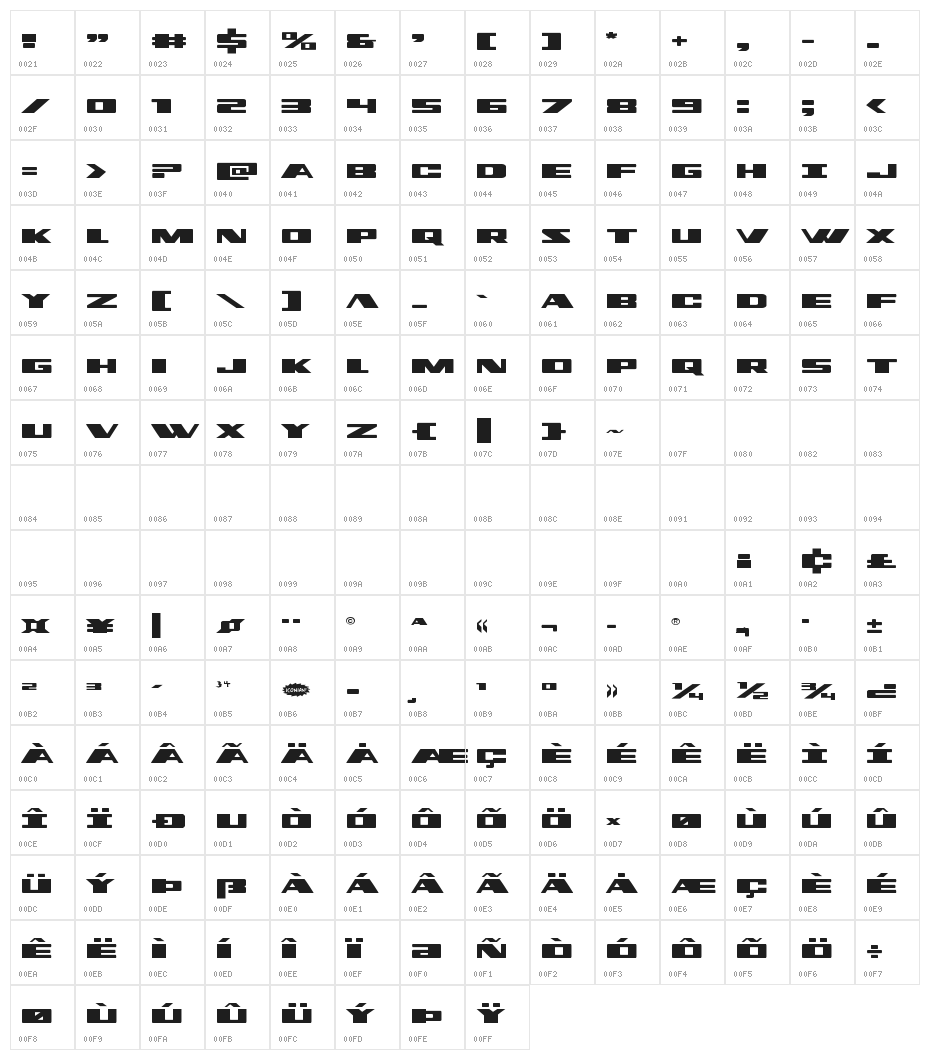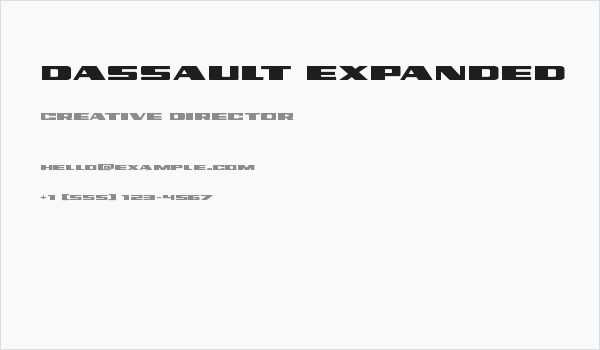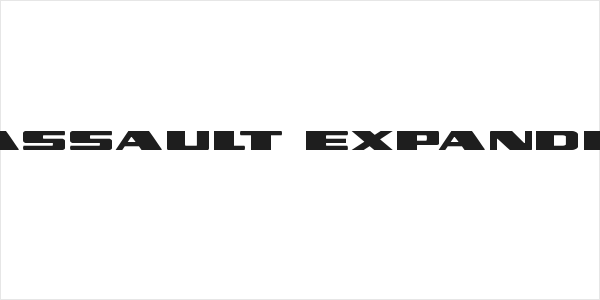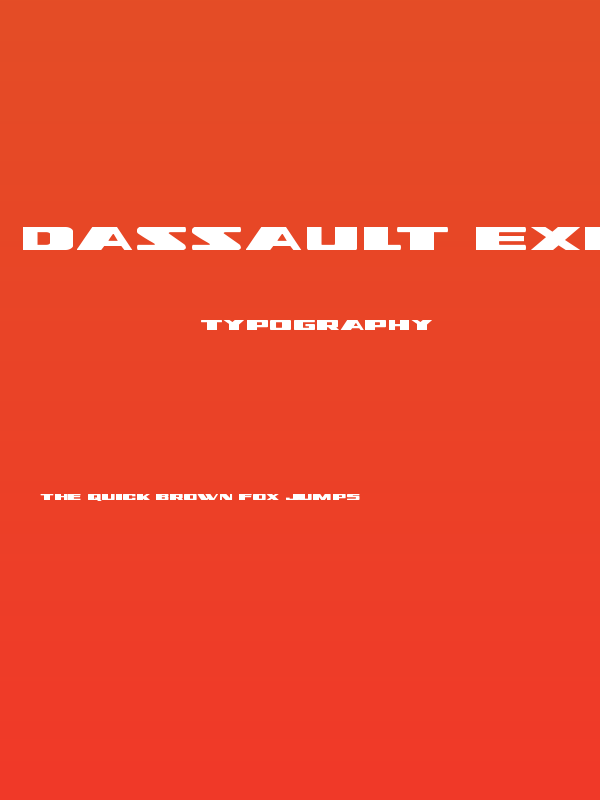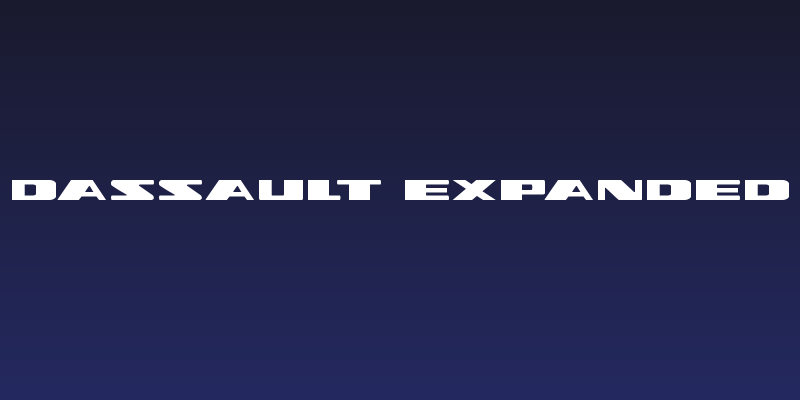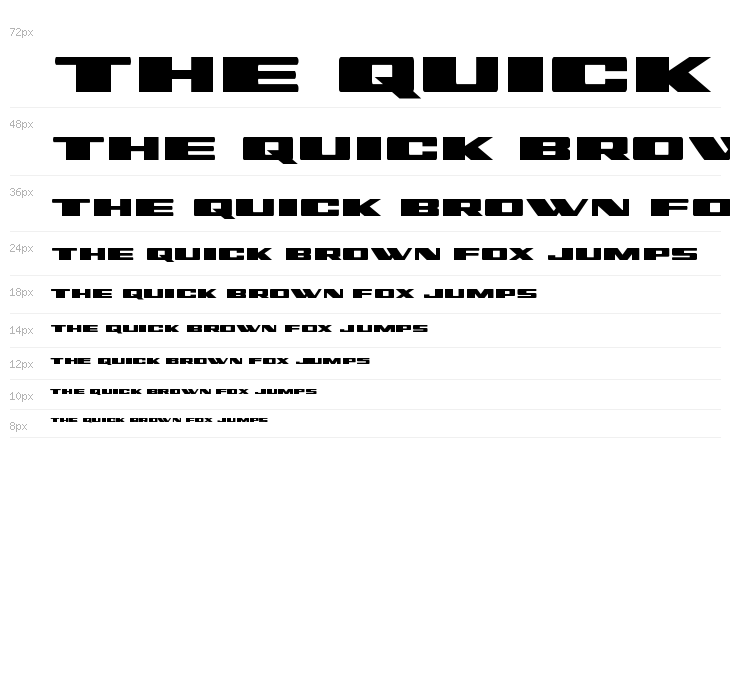
Dassault Expanded Font
✎ Futuristic
| Vorgeschlagene Projekte | Ideal for use in technology branding, sci-fi movie posters, video game titles, and modern advertising campaigns. |